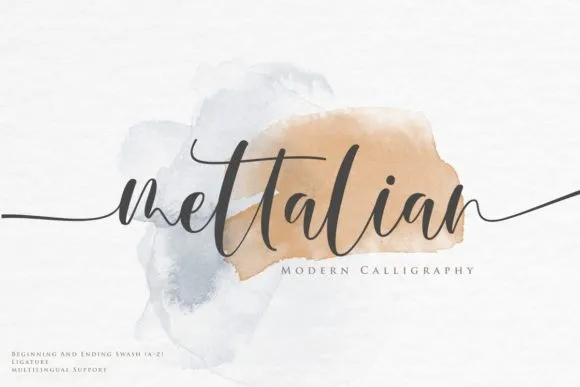
A Mettalian Font é uma fonte script moderna que traz uma pitada elegante ao seu design. Essa tipografia é perfeita para qualquer necessidade onde você deseja um toque de sofisticação, seja para criar marcas de marca, assinaturas criativas, convites de casamento, promessas de produto ou até mesmo logotipos e citações. Esta fonte moderna e simples mantém uma autenticidade única que não permite ela ser subtraída por sua simplicidade. Ela oferece um conjunto completo de letras minúsculas e maiúsculas, números e pontuação, símbolos para múltiplas línguas, e até mesmo swashes e ligaturas para dar uma personalidade extra à sua escrita. A Mettalian é perfeita para aqueles que procuram um toque sofisticado em seus projetos, seja você um designer gráfico ou criativo. Seja em seu próximo trabalho de marca, seu design de assinatura inovadora, seu convite de casamento personalizado ou até mesmo em sua frase de marketing para seus produtos, a Mettalian é uma opção perfeita para manter a elegância e originalidade do seu projeto.